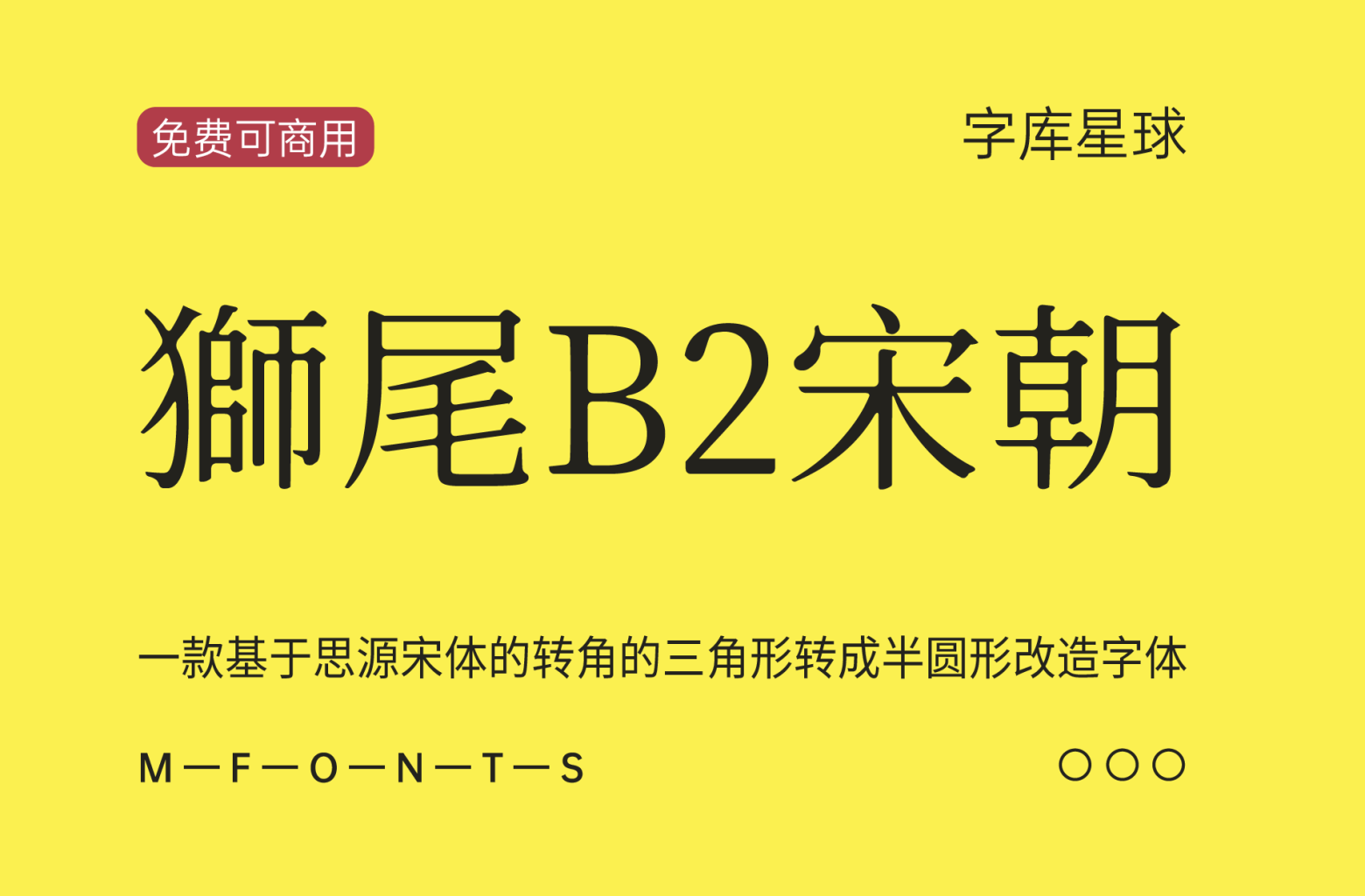
獅尾B2宋朝
狮尾B2宋朝字体是一款基于思源宋体的转角的三角形转成半圆形改造的免费可商用字体,仿佛墨晕或是稍微过曝的效果。支援简体中文、繁体中文、韩文与日文;欢迎大家自由应用、自由改作!
和思源宋体一样,支持7种的字重:
与其他字体的比较:
源云明体JP(1)、源云明体TW(2)、思源宋体(3)、狮尾B2宋朝(4)的比较:
• 在「肉」、「糸」、「女」、「辶」、「食」的笔画,狮尾比较相似台湾教育部推荐字体笔顺,适合教育用途。
• 在「草」部的笔画,狮尾是分开的二个部份。
• 字体里的「草字头部首」中间该不该连起来,「肉字旁部首」该不该变成「月」,要不要把手写习惯代入印刷字体?整体看来,会不会影响视觉的延伸性?会不会影响印刷的可行性与阅读的便利性?
字体后面的 SC,JP,TC是什意思?
• SC是 Simplified Chinese 简体中文,代表大陆习惯字形。
• TC是 Traditional Chinese 繁体中文,代表港台习惯的字形。
• JP是 Japanese 日文,代表日本习惯字形。
• 相同一个字,在不地区的书写方式可能会略有不同。